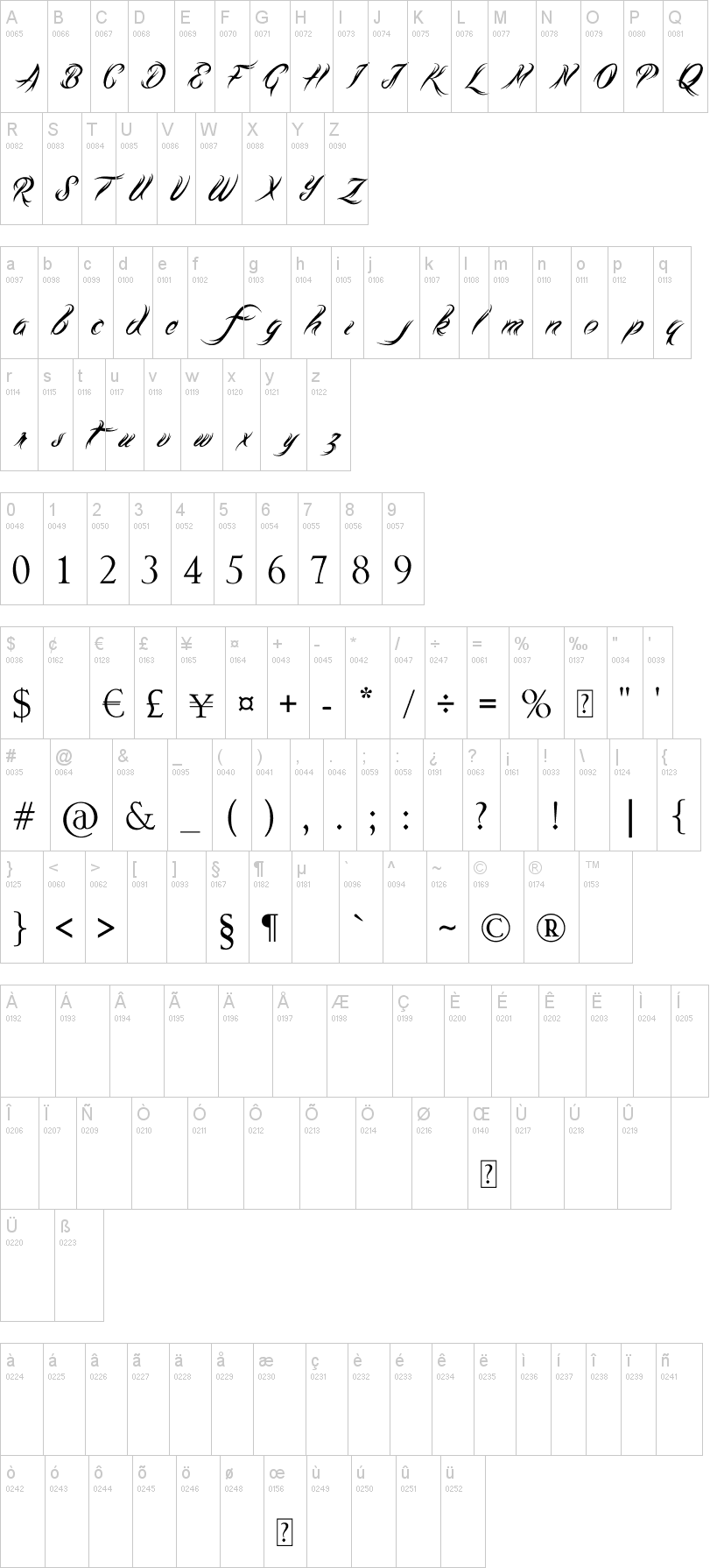
Tribal Script字体是一种拥有艺术感的手写字体,它具有独特的复古风格,适合用于拼贴画、海报、T恤等活动。这种字体最大的特点是其独特的笔画,它结合了传统的手写字体和现代设计元素,使每个字母都有自己的独特风格。它还具有可爱的设计,可以帮助你轻松创建拼贴画,以及其他艺术品。内容介绍
Tribal Script是一款非常不错的手写艺术字体,具有很好的视觉感,适合于文化类的宣传设计、商业类品牌的广告和产品包装设计以及个性化文字排版等较多场景。